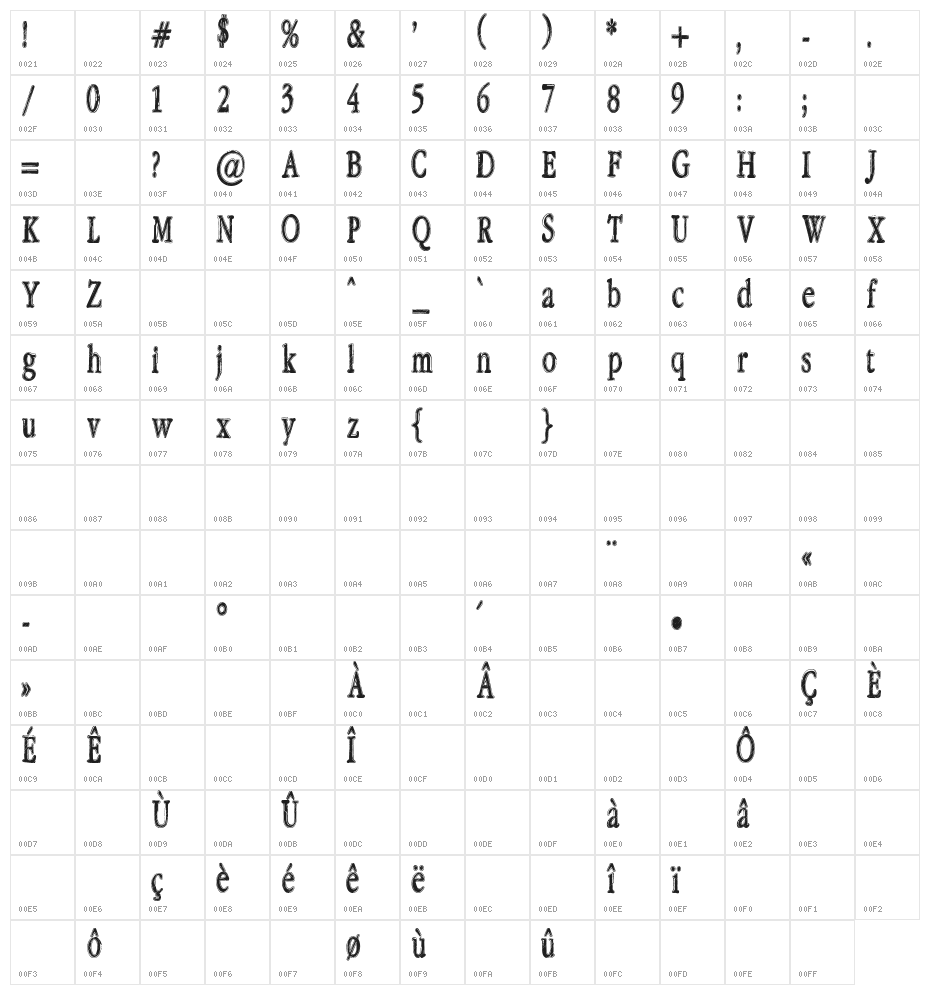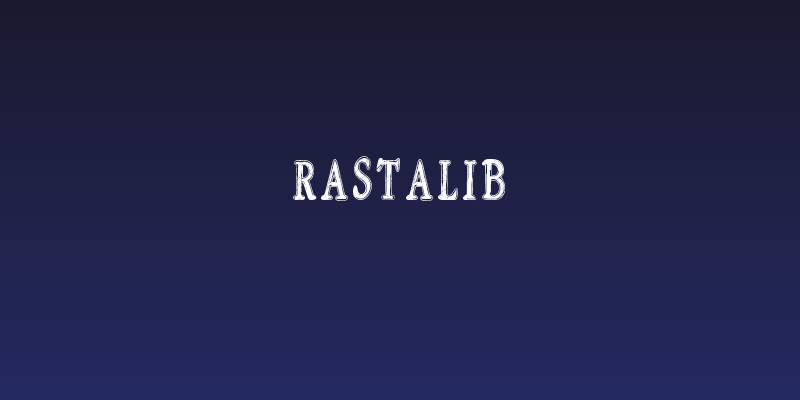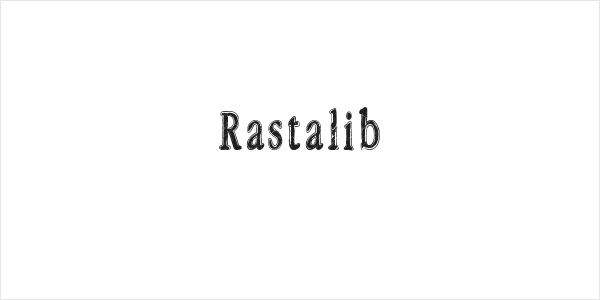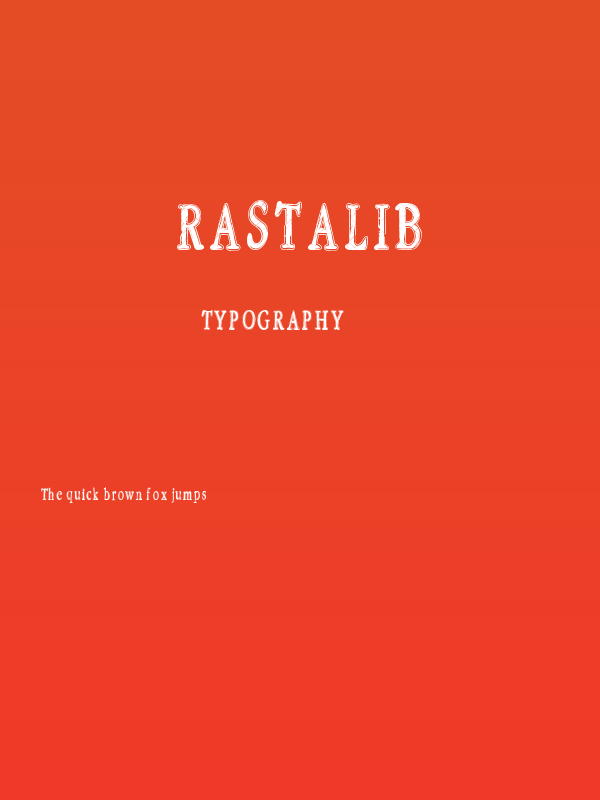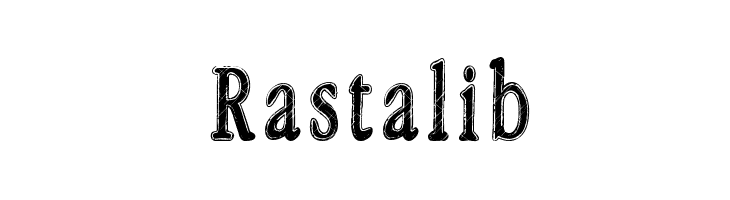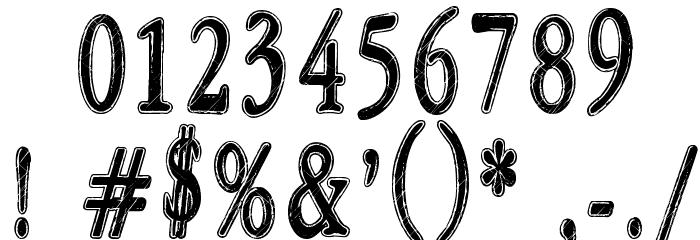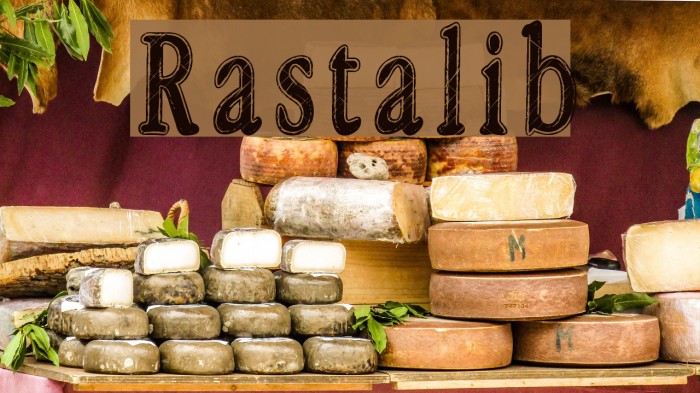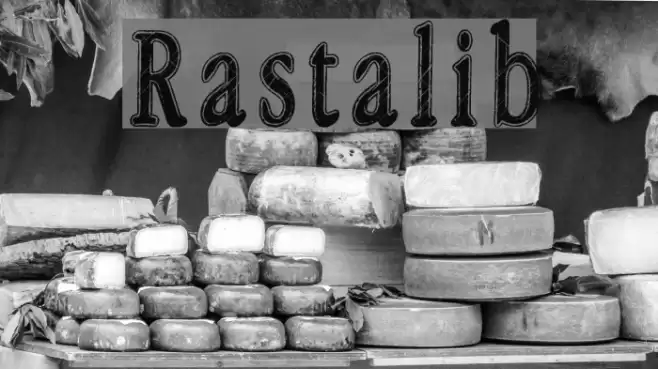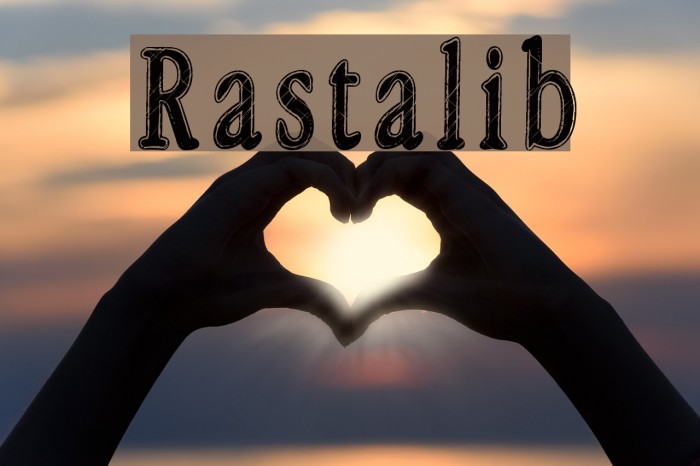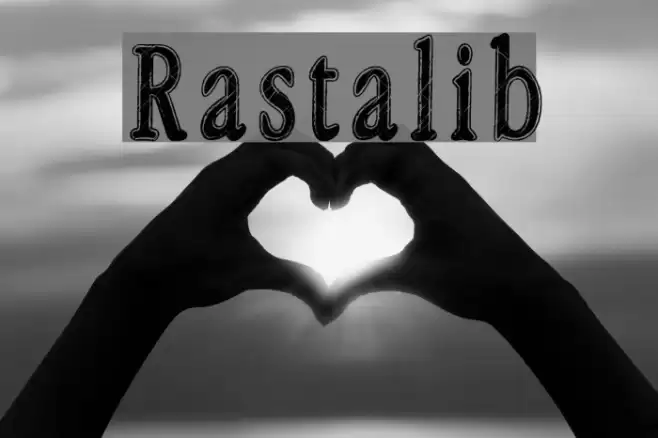
Rastalib Font
✎ Distorted Eroded
| Catégories | Distorted Eroded |
| Style général | Vintage, Decorative |
| Projets proposés | Ideal for vintage-themed posters, creative branding, eye-catching headlines, and artistic designs. |